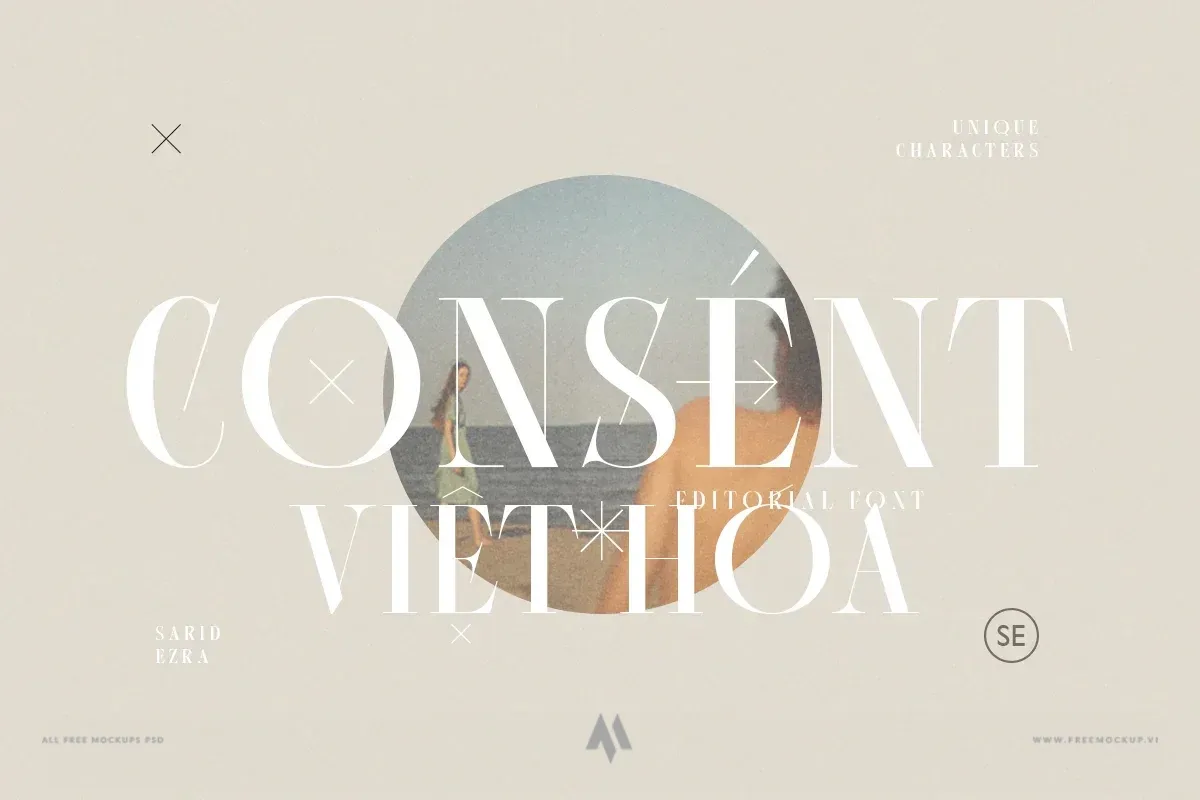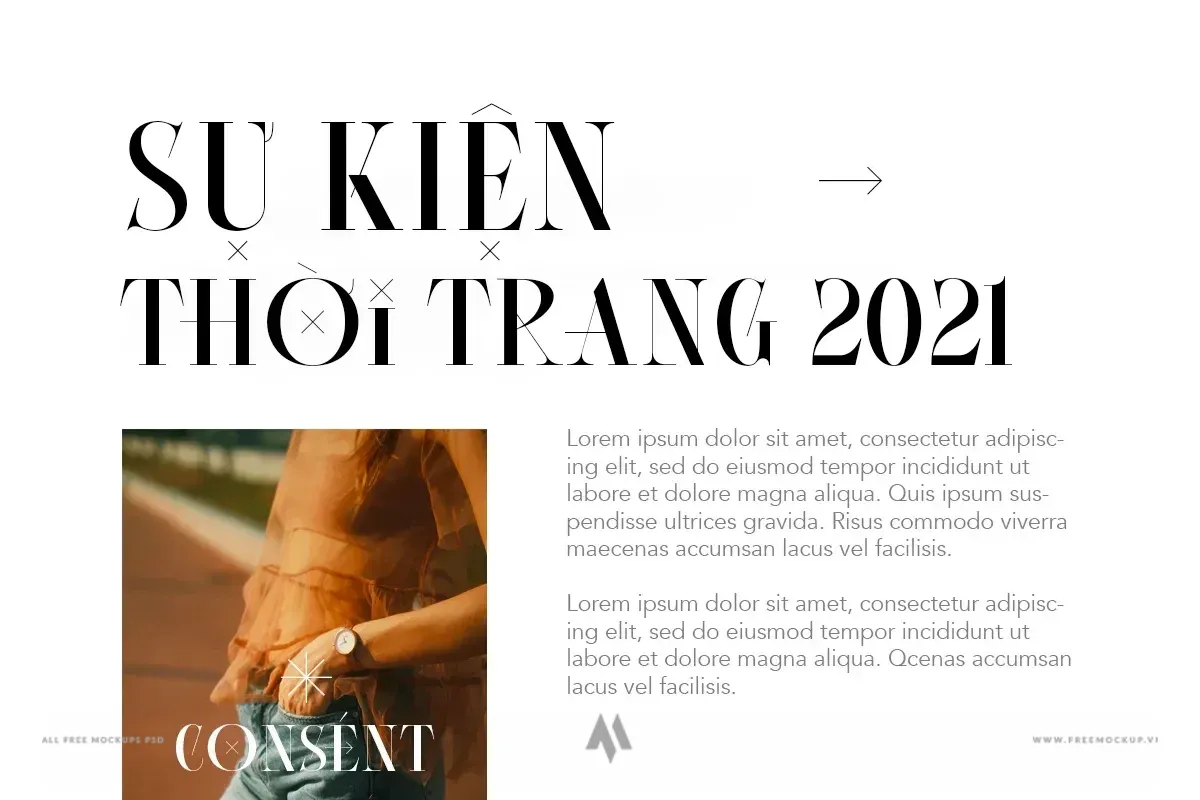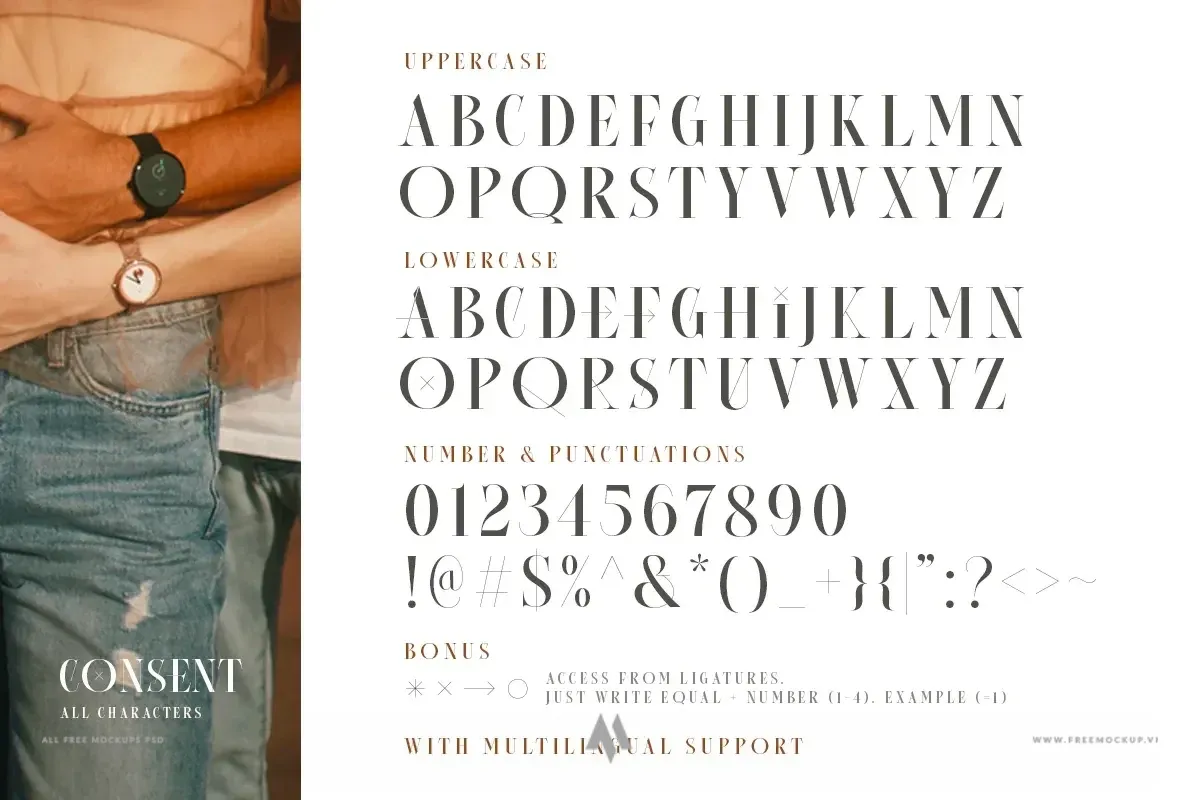
Font việt hóa Consent – font Serif
Consent Việt Hóa là bộ font chữ serif biên tập (Editorial Serif) độc đáo được thiết kế toàn bộ bằng hệ thống chữ hoa (all-caps), mang phong cách tối giản, sang trọng và hiện đại. Bộ font tạo ấn tượng mạnh mẽ cho các thiết kế đòi hỏi tính thẩm mỹ cao, độ sắc nét và tính thời thượng.
Đặc điểm nổi bật
• Phong cách Editorial cao cấp: Đường nét thanh thoát, tỉ lệ cân đối chuẩn mực, mang đến cảm giác trang nhã, chuyên nghiệp cho mọi ấn phẩm.
• Tính năng chuyển đổi linh hoạt: Dễ dàng thay đổi kiểu dáng chữ giữa chữ hoa và chữ thường để kích hoạt các nét biến thể (ligatures/alternates) mà không cần thao tác phức tạp.
Ứng dụng hoàn hảo trong thiết kế
• Biên tập & Xuất bản: Tiêu đề tạp chí thời trang, bìa sách nghệ thuật, tiêu đề bài viết (editorial headlines), lookbook.
• Bộ nhận diện thương hiệu: Logo cao cấp, typography nhãn hàng thời trang, mỹ phẩm, trang sức và kiến trúc.
• Quảng cáo & Truyền thông: Poster quảng bá, banner sự kiện sang trọng, hình ảnh visual cho chiến dịch marketing trên mạng xã hội.
• Bao bì & Ấn phẩm: Nhãn mác sản phẩm cao cấp, thiệp mời sự kiện, danh thiếp và catalogue.